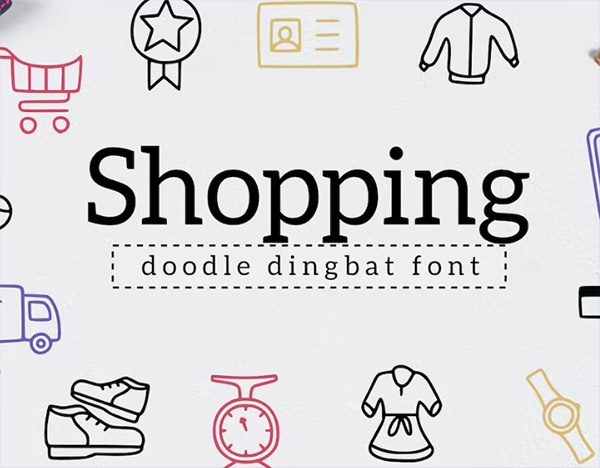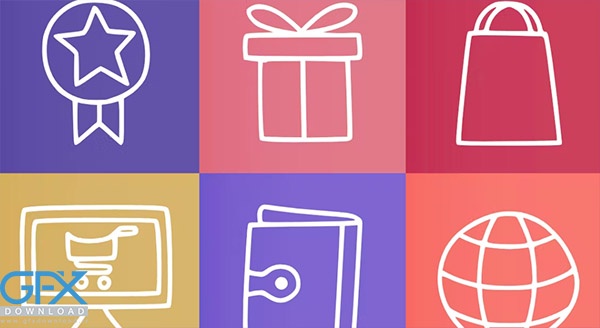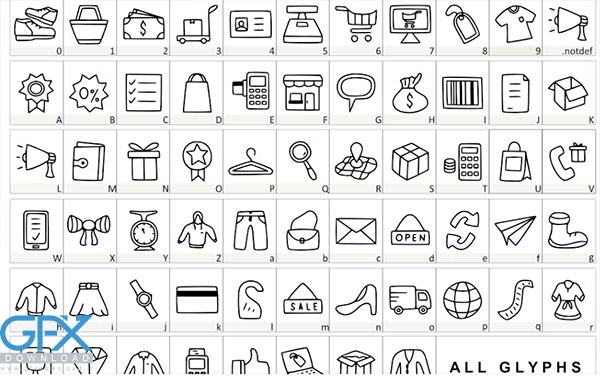
دانلود فونت رایگان کاراکترهای خرید Shopping Dingbat
دانلود رایگان فونت آیکون های خرید Shopping Dingbat
دانلود فونت رایگان انگلیسی کاراکترهای خرید Shopping Dingbat شامل 62 آیکون و نماد می باشد. Dingbat خرید ساده، مناسب برای بسیاری از پروژه‌ها، آرم‌ها، زیورآلات و غیره. دارای 62 نماد به عنوان پیش‌نمایش بالا.
فونت رایگان کاراکترهای خرید Shopping Dingbat
دانلود رایگان فونت کاراکترهای خرید Shopping Dingbat
دانلود رایگان فونت انگلیسی 62 کاراکتر و آیکون خرید Shopping Dingbat